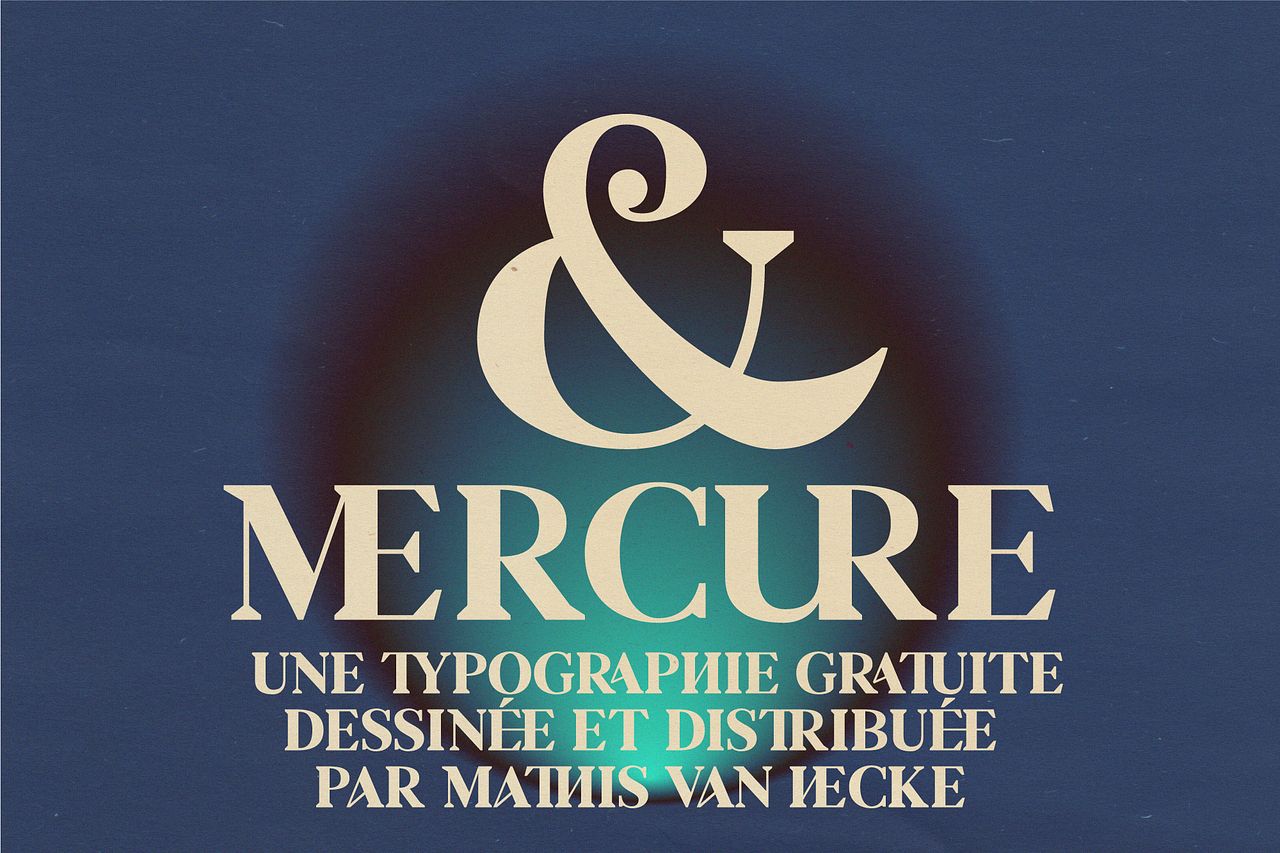
Mathis Van Hecke
MERCURE — typeface
La typographie MERCURE allie le poids du passé et la vision du futur grâce à son contraste marqué et ses formes imposantes. Ce caractère en majuscules capte l'essence du temps, offrant une esthétique qui défie les époques.